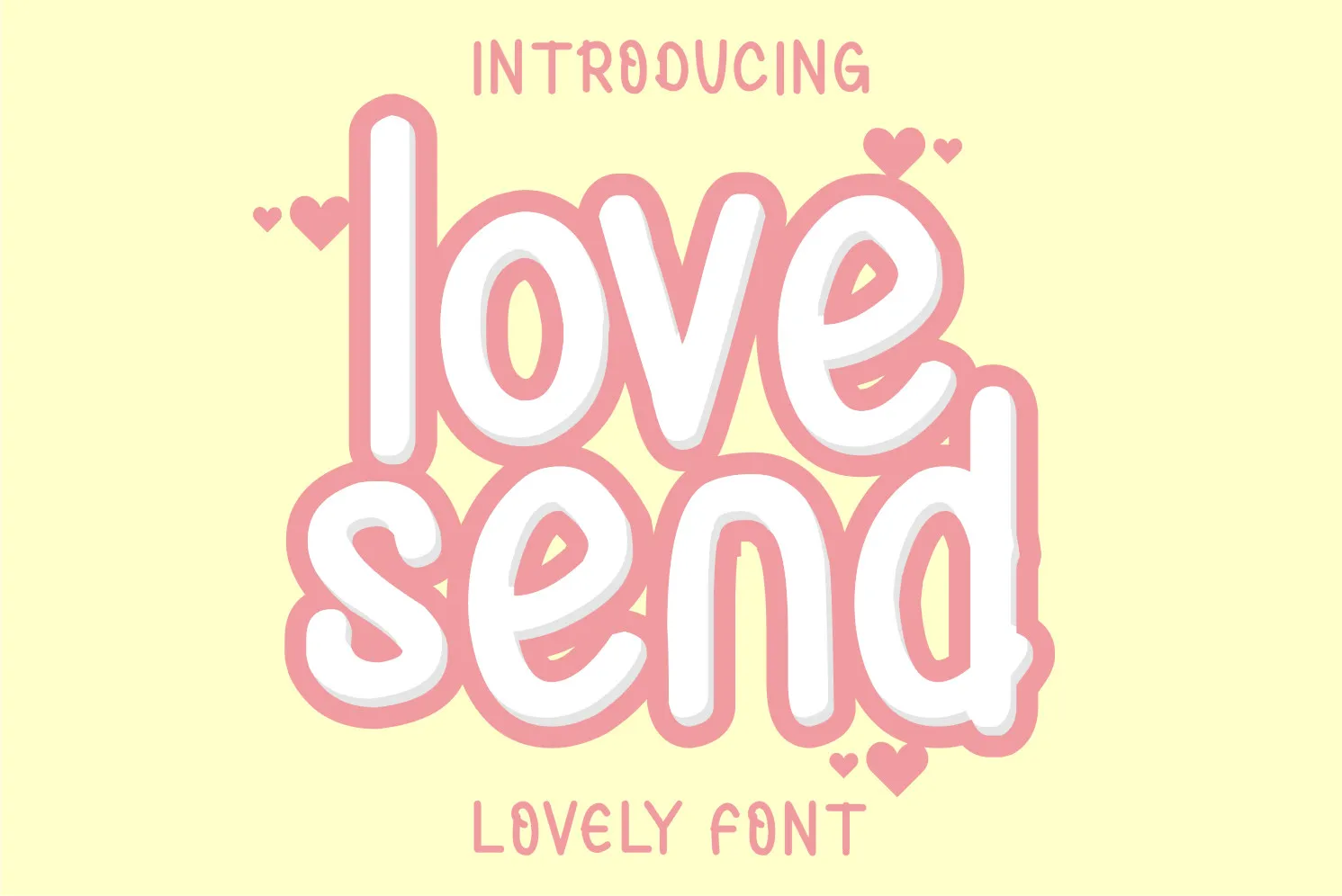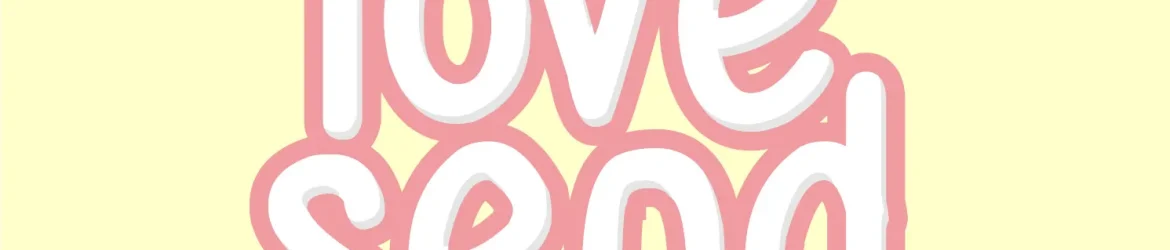
Love Send Font – Download Grátis
A fonte “Love Send Font” é uma escolha perfeita para quem busca uma aparição chamativa e elegante na sua próxima criação visual. Combinando elementos modernos com um toque de frescura, esta fonte foi projetada para transpor os tons de humor aos designs criados. É perfeitamente adaptável a muitas categorias de design, incluindo roupas desportivas e produtos personalizados para t-shirts ou camisetas, adesivos e até mesmo as mais modernas peças de moda. Adicionalmente, esta fonte é um ótimo candidato para criações visuais que precisam de um toque de personalização como logotipos e anúncios promocionais. Para designers aficionados com t-shirts, adesivos ou qualquer outra peça de roupa que você deseje fazer soar único, “Love Send Font” é uma solução perfeita. Seja para celebrar uma festa, unir amigos ou simplesmente expressar seu amor por um produto específico, a fonte certamente ajudará a tornar suas criações únicas e memoráveis. E se você está procurando uma fonte que combine estética elegante com um toque de irreverência, “Love Send Font” é definitivamente o item para você.